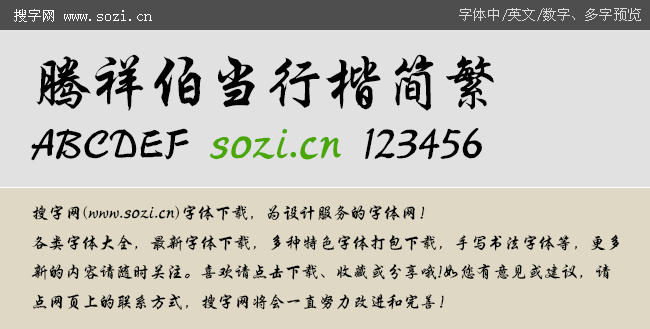
騰祥伯當(dāng)行楷簡繁合集
搜字網(wǎng)提供一款騰祥伯當(dāng)行楷簡繁合集中文藝術(shù)字體下載,騰祥伯當(dāng)行楷是一款漂亮的行楷字體,書寫流暢,字形瀟灑大方。適合數(shù)字媒體、包裝設(shè)計(jì)、廣告設(shè)計(jì)、網(wǎng)頁設(shè)計(jì)等設(shè)計(jì)場(chǎng)合使用。